Как различить строчные «ц» и «щ» в рукописном шрифте: хвост, ритм и проверка
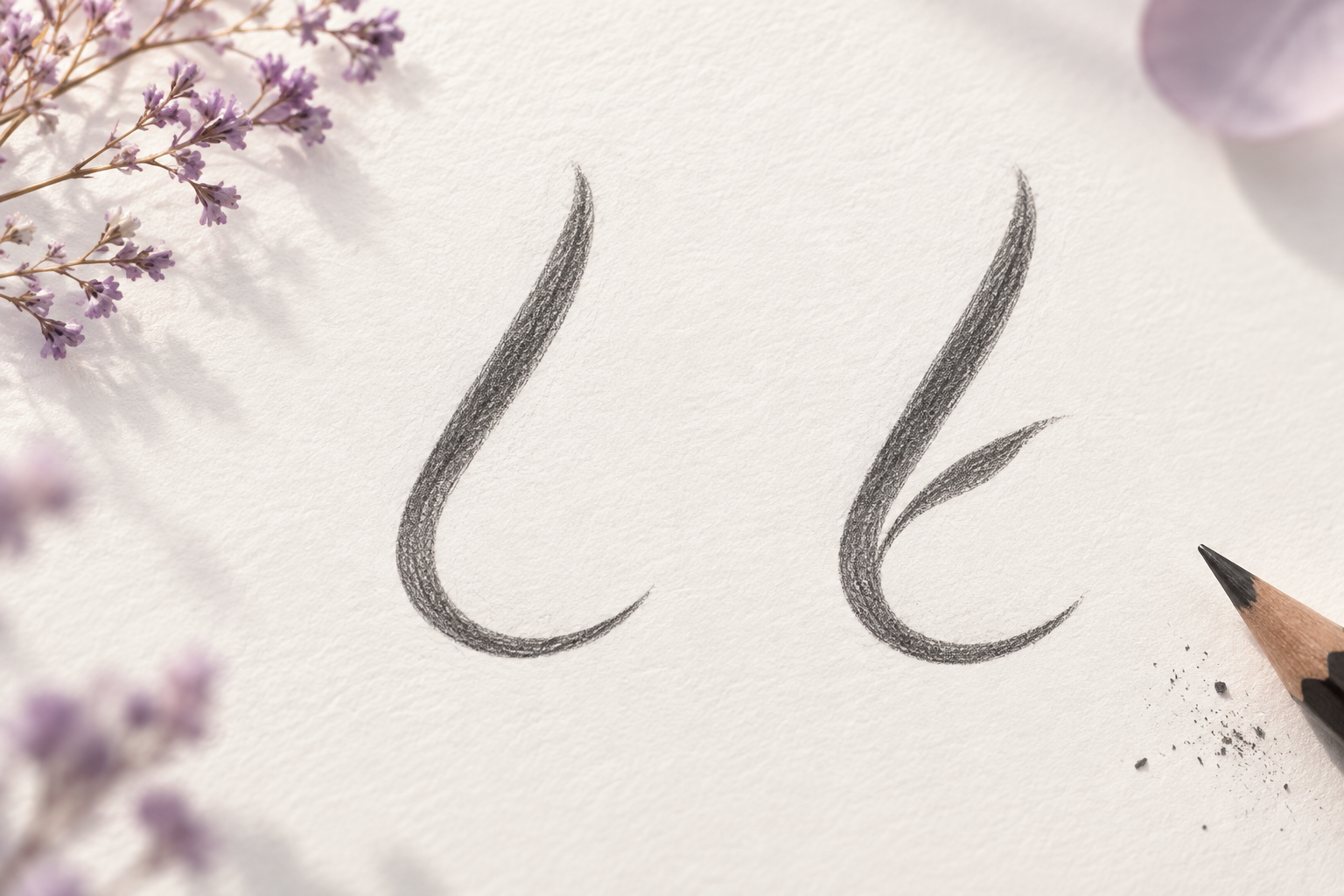
Строчные «ц» и «щ» в рукописном шрифте легко спутать, если сравнивать только верхнюю часть: обе буквы могут строиться на похожем ритме коротких штрихов и иметь вынос ниже строки. Различие задают не декоративные «хвосты», а число и расположение элементов, их соединение с основой и устойчивый силуэт. Ниже — способ проверить пару отдельно, в словах и после уменьшения, чтобы поправить рисунок без механического утяжеления одной буквы.
Почему пара сбивает читателя
У обеих букв есть повторяющиеся короткие вертикальные или наклонные движения, а в скорописном рисунке соединительные дуги могут сгладить границы между ними. Если смотреть на крупный знак отдельно, автору понятен замысел: он знает, где провёл перо и что хотел написать. Читатель видит не процесс, а готовый силуэт. Поэтому намеренно добавленный тонкий штрих может исчезнуть при уменьшении, а слишком длинный нижний вынос — стать главным признаком буквы и нарушить ритм строки.
Важно не закреплять единственную «правильную» каллиграфическую форму. Рукописный шрифт может быть более связным, геометричным, округлым или угловатым; способы соединения отличаются. Но внутри одной гарнитуры читатель должен распознавать букву по нескольким согласованным признакам. Если единственным отличием остаётся едва заметная петля, доступность формы зависит от качества экрана, масштаба и соседних букв.
Сначала разберите конструкцию, затем оптику. В обычной строчной кириллице у «щ» есть дополнительный элемент по сравнению с близкой «ш», а у «ц» есть нижний выносной штрих. В конкретном почерке эти элементы могут соединяться непривычно, поэтому проверяйте не школьную схему по памяти, а собственную матрицу: сколько основных движений видно, откуда начинается нижний элемент и к какой части он относится. Смысловой контекст помогает в слове, но он не исправляет плохо различимый глиф.
Составьте паспорт двух букв
Возьмите несколько вариантов каждой буквы из набросков и опишите их нейтрально, без оценок «красивее» или «понятнее». Для каждой версии запишите число основных штриховых движений, точки входа и выхода, высоту корпуса, ширину, наклон, направление соединений и форму нижнего выноса. У «ц» отметьте, как именно продолжение уходит ниже строки; у «щ» проследите, какой элемент добавляет отличительный силуэт и где заканчивается нижняя часть. Если в вашей модели «щ» получает нижний штрих другим способом, зафиксируйте именно этот способ.
Полезен не только перечень деталей, но и карта зрительного приоритета: что замечается первым при беглом взгляде? Если сначала видны одинаковые «зубцы», а различающая часть теряется, отстройте одну из характеристик. Это может быть яснее обозначенный переход к хвосту, иной угол соединения, немного другая ширина или более открытая форма просвета. Меняйте один параметр за раз: иначе после правки будет трудно понять, что улучшило чтение.
- Нарисуйте по 5–7 вариантов «ц» и «щ» рядом в одинаковой высоте и толщине.
- Подпишите конструктивные элементы словами, например «основа», «переход вниз», «добавочный штрих».
- Обведите только внешний контур и сравните силуэты без внутренних деталей.
- Попросите человека, не видевшего эскизов, назвать букву до того, как вы объясните задуманную форму.
Как настроить нижний вынос «ц»
Нижняя часть «ц» — сильная подсказка, но она должна восприниматься продолжением буквы, а не случайной чертой от соседнего знака. Проверьте точку выхода: если линия начинается далеко от основного тела или пересекает соединение так, что образуется отдельный узел, форма выглядит сломанной. Если вынос слишком короткий, он может слиться с базовой линией; если непропорционально длинный — цеплять взгляд и казаться декоративным элементом.
Сравните угол и характер штриха с другими элементами гарнитуры. В мягком округлом алфавите резкий крючок будет выглядеть чужим, а в угловатой системе округлый хвост может потерять ясность. Не обязательно копировать форму «у» или «д»: задача в том, чтобы нижний штрих имел понятную логику движения, не превращая разные буквы в один повторяющийся жест. Проверьте, не создаёт ли соединение с последующей буквой иллюзию дополнительной петли.
Для правки удобно смотреть на букву в трёх видах: нормальный контур, залитый силуэт и уменьшенный растр. В контуре заметны узкие просветы и неаккуратные стыки; в заливке — общий баланс; в растре — то, что останется при реальном использовании. Если нижнее продолжение пропадает в растре, сначала проверьте толщину и форму соединения на рабочем размере. Не спасайте его чрезмерным удлинением: такая правка обычно портит пропорции в крупном кегле.
Как не перегрузить «щ»
Дополнительный штрих помогает отличить «щ», пока он остаётся самостоятельным и читаемым. Когда он слишком короткий, наклонён в сторону соседнего элемента или сливается с ним, зрительно получается та же основа, что у другой буквы. Когда он чрезмерно широк или утолщён, «щ» становится пятном, а внутренние просветы закрываются. Ищите минимальную разницу, которую видно без разглядывания, но которая не меняет общий характер алфавита.
Сравнивайте число элементов не линейкой, а по устойчивым визуальным опорам. В свободном рукописном стиле допустимы небольшие отклонения, но добавленная деталь должна оставаться в ожидаемом месте и поддерживать направление чтения слева направо. Если авторский жест требует, чтобы штрих «щ» начинался необычно, повторите его в нескольких словах и проверьте, не напоминает ли он знак препинания, случайный росчерк или начало следующей буквы.
Проверьте внутренние промежутки: одинаковая толщина штрихов не гарантирует одинаковую читаемость. Плотная «щ» может выглядеть тяжелее «ц» даже при равной площади контура, особенно если нижний вынос закрывает просвет. Иногда достаточно чуть развести элементы или изменить их наклон. Если приходится заметно уменьшать одну букву, чтобы уместить детали, пересмотрите ширину и построение всей пары, а не только отдельный штрих.
Проверьте буквы в словах, а не только в таблице
Изолированное сравнение показывает конструкцию, но не проверяет соединения. Составьте короткие тестовые строки с позициями, где «ц» и «щ» встречаются в начале, середине и конце слова. Используйте настоящие слова, а рядом добавьте бессмысленные сочетания, чтобы контекст не подсказывал ответ. Например, «улица», «цвет», «молодцы» и «щука», «ищу», «плащ» дают разное окружение и разное положение нижнего элемента.
Обязательно поставьте спорную букву рядом с формами, которые могут усиливать путаницу: «ш», «и», «п», а также с наклонными соединительными штрихами вашего алфавита. Это не значит, что нужно проверять все сочетания кириллицы сразу. Достаточно увидеть, не превращает ли присоединённый выход из предыдущего знака отличительную часть «щ» в лишний зубец и не маскирует ли вход в «ц» её нижнее продолжение. Для связного шрифта дополнительно проверьте два-три типичных перехода до и после каждой буквы.
Проведите простую слепую проверку: покажите несколько слов на короткое время, уберите образец букв и попросите читателя прочитать их вслух. Затем задайте один точный вопрос: «На каком месте пришлось остановиться?» Не подсказывайте, какая буква должна быть. Ошибка чтения полезнее общей оценки «вроде нормально», потому что показывает конкретный стык или размер, который стоит исследовать. Повторите пробу с другим читателем после правки.
Проверьте масштаб, контраст и строку
Уменьшайте образец ступенчато: рабочий размер, один шаг меньше и размер, в котором надпись действительно будут читать. Если шрифт предназначен для крупных подписей, не требуйте от него поведения мелкого книжного текста; всё же полезно знать точку, где различие распадается. При растрировании тонкие соединения могут слипаться или пропадать в зависимости от пиксельной сетки и сглаживания. Оцените знак и на светлом фоне, и в реалистичном макете с соседним текстом.
Не судите по одной фотографии экрана или изображению, увеличенному браузером: масштабирование может сгладить мелкие детали. Для сравнения экспортируйте несколько одинаковых строк при одном размере и одинаковом межбуквенном интервале. Смотрите сначала на расстоянии чтения, затем увеличьте изображение, чтобы найти причину. Эта последовательность не даёт увязнуть в микродефектах, которые читатель никогда не заметит, и одновременно помогает обнаружить реальный провал различимости.
Если вы собираете авторский шрифт из шаблона, сравнивайте версии в одном и том же тестовом наборе. Сохраните исходный вариант, поменяйте только «ц» или только «щ», затем повторите слепую пробу. После успешного изменения посмотрите на целую строку: исправленная буква может стать шире, изменить интервал или нарушить ритм. Так локальная победа не создаст новую проблему на уровне слова.
Пошаговая проверка перед фиксацией рисунка
- Зафиксируйте для каждой буквы число основных движений, соединения и положение нижних элементов.
- Нарисуйте несколько вариантов одной пары в одинаковых пропорциях; меняйте только одну характеристику.
- Сравните внешний силуэт, заполненную форму и внутренние просветы.
- Проверьте «ц» и «щ» в коротких словах и в нейтральных сочетаниях без смысловой подсказки.
- Уменьшите строки до реального размера использования и посмотрите их на обычном экране или распечатке.
- Проведите слепое чтение, запишите места остановок и исправьте причину, а не только симптом.
- Повторите проверку после экспорта, чтобы убедиться, что форма не распалась при преобразовании.
Первый риск — опираться только на смысл слова. Читатель действительно часто угадает «ц» в «улице», но это не подтверждает, что сама форма различима. Второй — удлинять хвост, пока он не станет очевидным. В итоге знак теряет баланс, а хвост начинает восприниматься как самостоятельная завитушка. Третий — лечить «щ» утолщением добавочного штриха: при уменьшении просветы могут закрыться, и различие станет хуже, хотя деталь выглядит заметнее в крупном виде.
Ещё одна ошибка — исправлять обе буквы одновременно. Тогда автор сравнивает уже новую систему и не понимает, какая перемена помогла. Сохраните контрольную пару и меняйте по одному параметру: длину, угол, ширину, интервал или точку соединения. Не делайте вывод по увеличенному фрагменту без проверки строки. И не считайте рукописную вариативность дефектом: единообразие означает повторяемые правила, а не математическую идентичность каждого штриха.
Наконец, не просите читателя просто «оценить буквы». Дайте ему слова, уберите подсказку о целевой форме и спросите, где возникла пауза. Такая проверка не заменяет чтение целого шрифта, но превращает субъективное ощущение в практическую задачу: какой элемент теряется, при каком размере и с каким соседством.
Контрольный список
- У «ц» нижнее продолжение явно связано с основой и не выглядит случайным росчерком.
- У «щ» добавочный элемент виден, но не закрывает просвет и не утяжеляет весь знак.
- Пара сохраняет общий наклон, толщину и характер остальных букв.
- Слова читаются без подсказки автора и без опоры только на контекст.
- Различие остаётся заметным в том размере и на том носителе, для которого создаётся шрифт.
- После экспорта и уменьшения не исчезает ключевой признак ни одной буквы.
Чем обычно различаются строчные «ц» и «щ»?
У пары сходна часть основного силуэта, но различаются строение элементов и нижняя часть знака. В рукописном шрифте важно проверить, как добавочный штрих «щ» и вынос «ц» соединяются с телом буквы: одной теоретической схемы недостаточно, если конкретный авторский рисунок устроен иначе.
Можно ли сделать хвост «ц» длиннее для ясности?
Можно, если короткий выход действительно теряется в нужном размере. Сначала проверьте точку выхода, угол, толщину и положение относительно базовой линии. Чрезмерная длина часто ломает ритм строки и превращает функциональный штрих в декоративный, поэтому оценивайте правку в словах и при реальном масштабе.
Нужно ли полностью убирать соединения в рукописном шрифте?
Нет. Связность — часть характера гарнитуры, и её не нужно жертвовать автоматически. Следует лишь убедиться, что входящий или исходящий штрих не маскирует отличительный элемент и не создаёт ложный дополнительный зубец. Для этого проверьте несколько типичных сочетаний, а не только отдельные глифы.
Как проверить различимость, если автор уже знает ответ?
Попросите человека, не знакомого с рисунками, быстро прочитать короткие слова без предварительного показа алфавита. Запишите именно места остановок или неверных прочтений. Затем повторите проверку после одной конкретной правки, сохранив тот же набор слов и размер.
Почему буквы хорошо различаются крупно, но путаются в маленьком размере?
Тонкий соединительный штрих может исчезнуть при растрировании, а близкие элементы — слиться из-за масштаба и сглаживания. Сравните залитые контуры и строки при фактическом размере. Правьте толщину, расстояние или соединение постепенно, чтобы не повредить пропорции в крупном кегле.
Стоит ли ориентироваться на одну каллиграфическую форму?
Нет: рукописные шрифты используют разные манеры, и вариантов построения несколько. Надёжнее определить правило внутри собственной гарнитуры и применять его последовательно. Если нужна проверка знаков в полном наборе, инструмент Fontgenerator поможет собрать и оценить результат авторского шрифта.
Чтобы уверенно различать «ц» и «щ», сначала опишите конструкцию, затем проверьте силуэт и соединения, а после — прочитайте слова в реальном масштабе без подсказки. Правьте один параметр за раз и сохраняйте контрольные строки: так выразительная рукописная форма останется узнаваемой, а нижние элементы будут работать как часть буквы, не превращаясь в украшение.